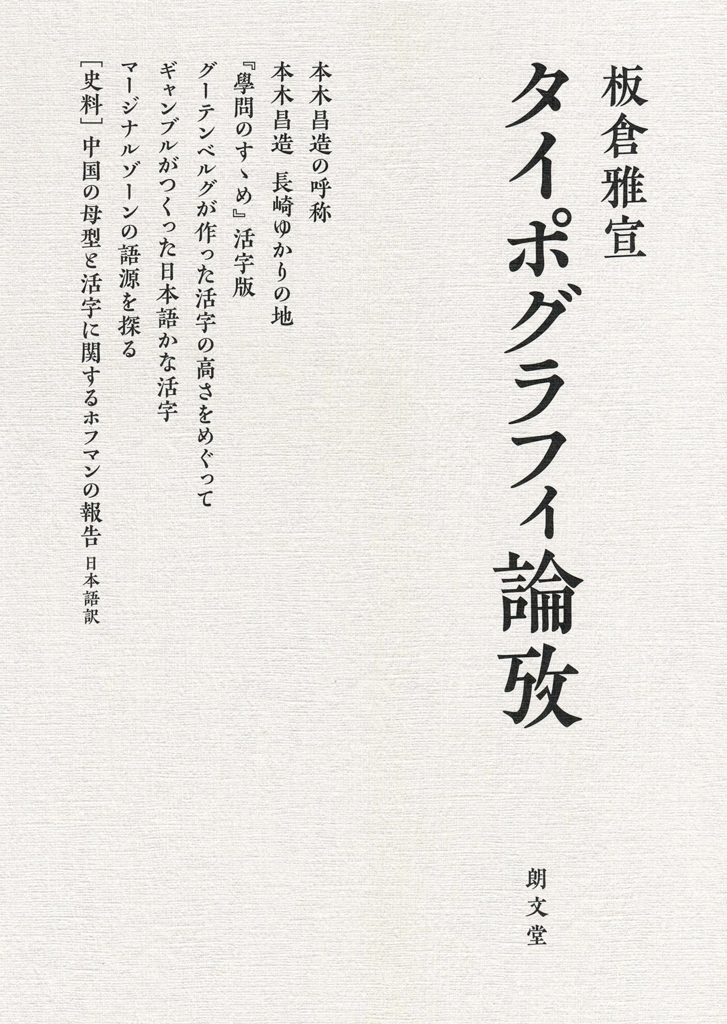
タイポグラフィ論攷
2009年第二回本木昌造賞受賞の板倉雅宣氏著書の「タイポグラフィ論攷」が朗文堂から2017年6月19日に発売された。
〔著者 まえがきより抜粋〕
「本木昌造の呼称」これは本木昌造の読みが、「もとき」か「もとぎ」かという問いかけにこだわって、調べたもので、長崎歴史文化博物館、神戸市立博物館、江戸東京博物館、長崎史談会等々を調査し、東京大学史料編纂所のイサベル・ファン・ダーレン女史にも声をかけて、本木昌造の自筆欧文サインの発見に協力をいただきました。本木昌造の祖父の代までは「もとぎ」のサインがみつかり、親の代から「もとき」と名乗っていることがわかったという記録です。
「本木昌造 長崎ゆかりの地」は、2009年に、タイポグラフィ学会の本木昌造賞を戴いた時に会場で配布したもので、2003年9月に朗文堂の片塩二朗氏と長崎を訪ねたときに巡ったときの写真を添えてあります。この時の受賞記念メダルには「MOTOGI」と刻印されています。
「『學問のすゝめ』活字版」は、東書文庫に全冊が収蔵されているのと、同じく東書文庫に所蔵されている『文部省雑誌 第一号』(明治7年1月刊)と、『学問のすすめ』初版の活字版の活字サイズが同じであることから調べ始めたことです。福沢諭吉と親交のあった芝神明前の尚古堂の岡田屋嘉七が関係したのかもしれません。
「ギャンブルが作った日本語かな活字」明治初年に日本政府から要請を受けて、上海美華書館のウィリアム・ギャンブルが鋳造活字の製法を本木昌造に伝授しました。フルベッキとヘボンのやりとりが興味深いと思われます。美華書館のウィリアム・ギャンブルを招聘した経緯は後藤吉郎氏が「長老派教会歴史協会」で「アメリカ・プレスビテリアン教会・海外伝道会記録」のマイクロフィルムを調査されていますが、一部を公表されていますが、詳細は不明です。日本政府から$.5,000.を受け取ったとかいう記録が公開されるのを楽しみにしています。
板倉雅宣Profile●1932年東京上野生まれ。1957年千葉大学工学部工業化学科印刷専攻卒業。東京書籍株式会社入社。1990年東京書籍印刷株式会社常務取締役。1994年東京製版株式会社社長。1999年退任。受賞:2007年感謝状(印刷図書館)。2009年第二回本木昌造賞(タイポグラフィ学会)(本データはこの書籍が刊行された当時に掲載されていたもの)